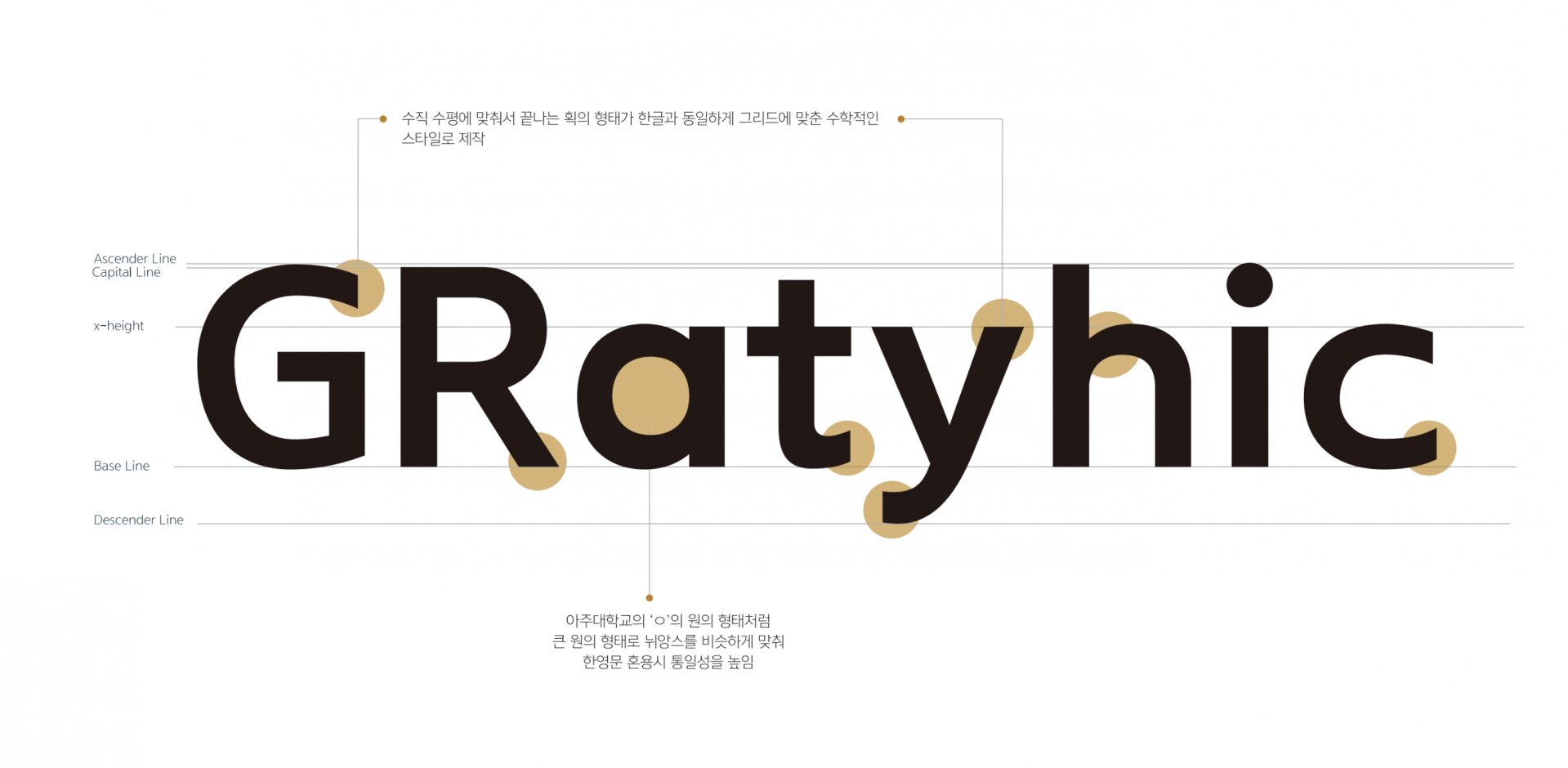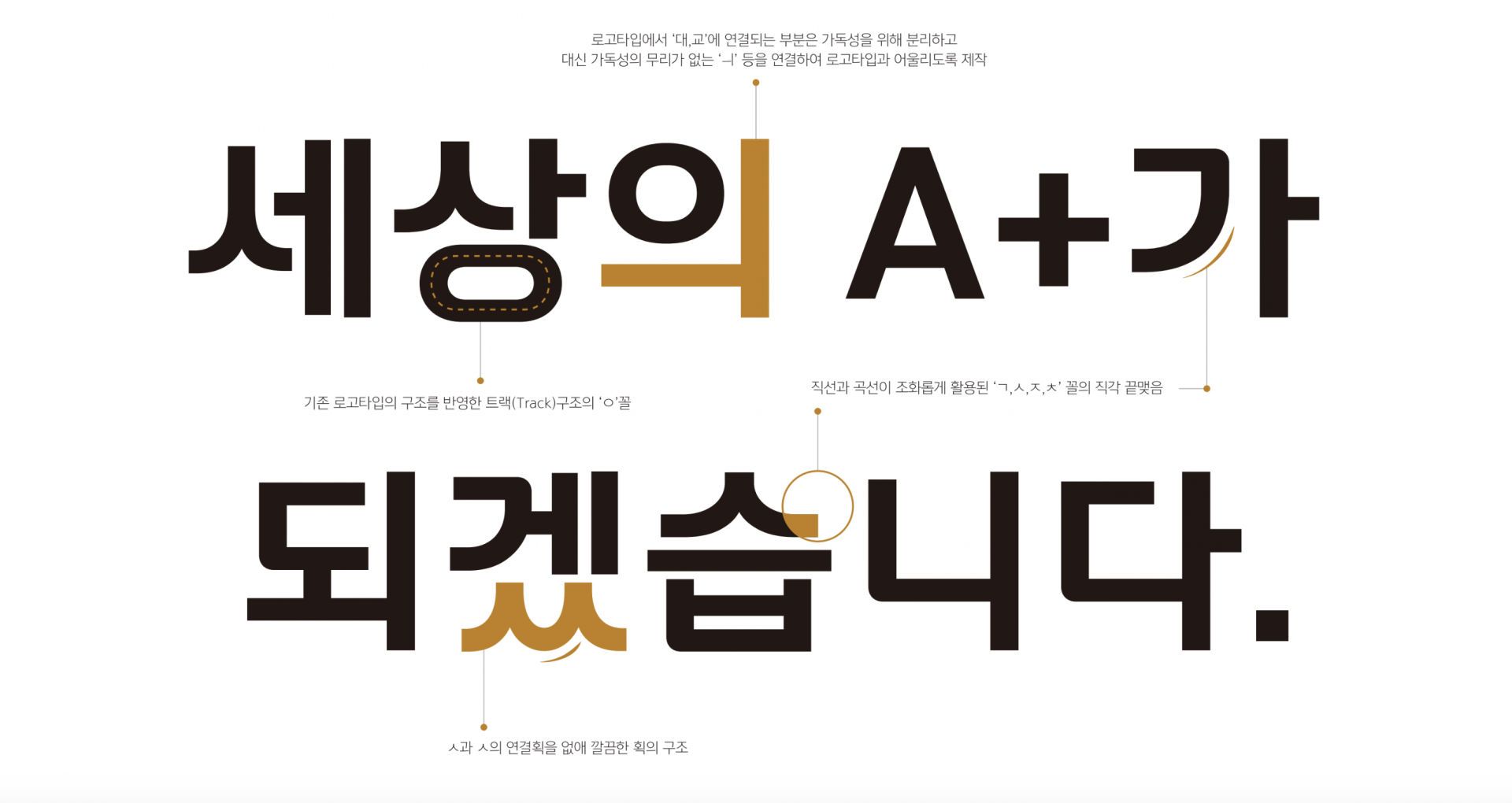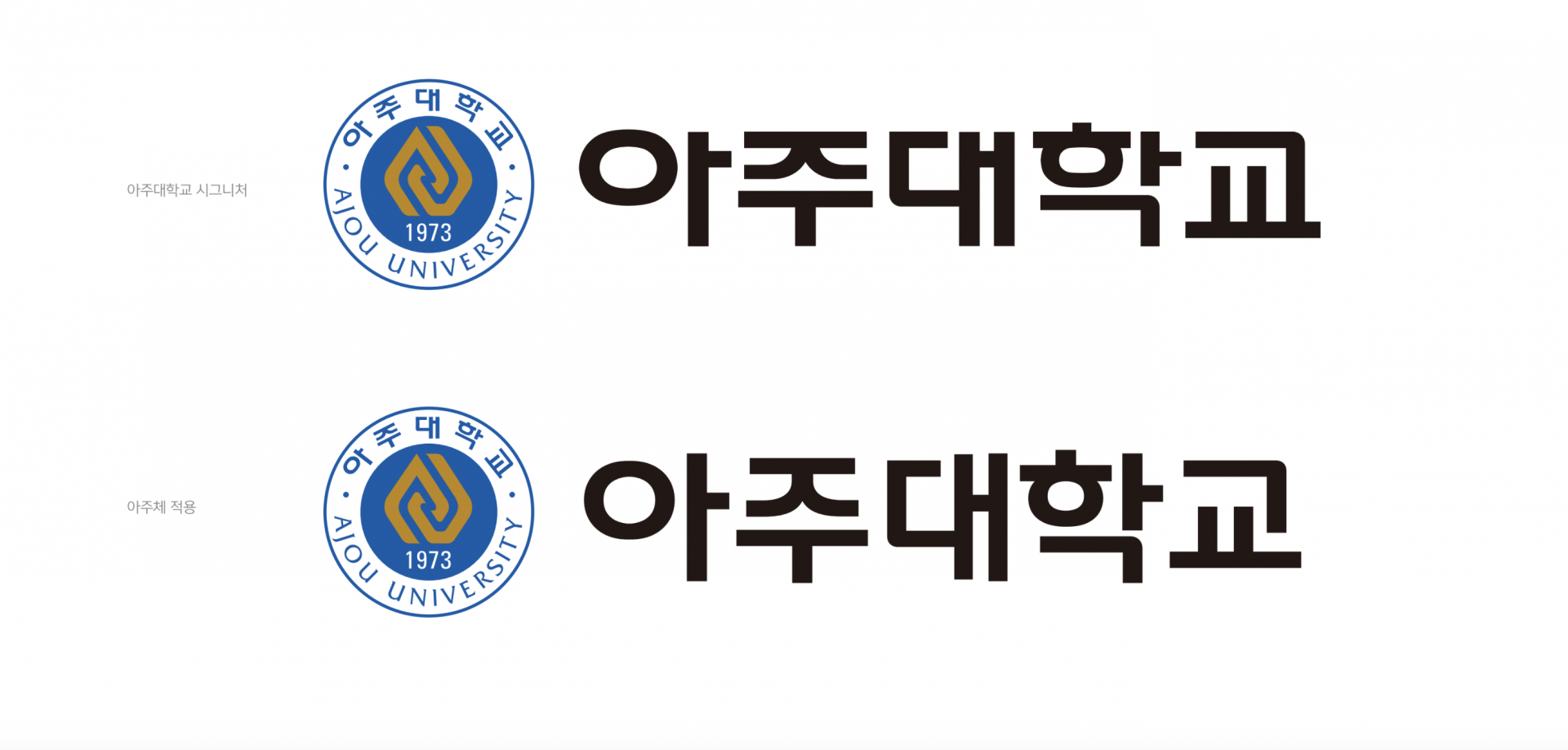
아주대학교 [아주체]
아주대학교 전용서체 [아주체]는 아주대학교의 교표 및 시그니처 시스템에서 사용하는 '아주대학교'로고타입과 어울릴 수 있도록 디자인하였다. 개교 50주년을 맞이하여 아주인(人)의 자긍심을 높이고 미래 100년 역사를 창조하는 비전에 어울리도록 2023년에 걸맞는 현대적인 미감을 반영하였다.